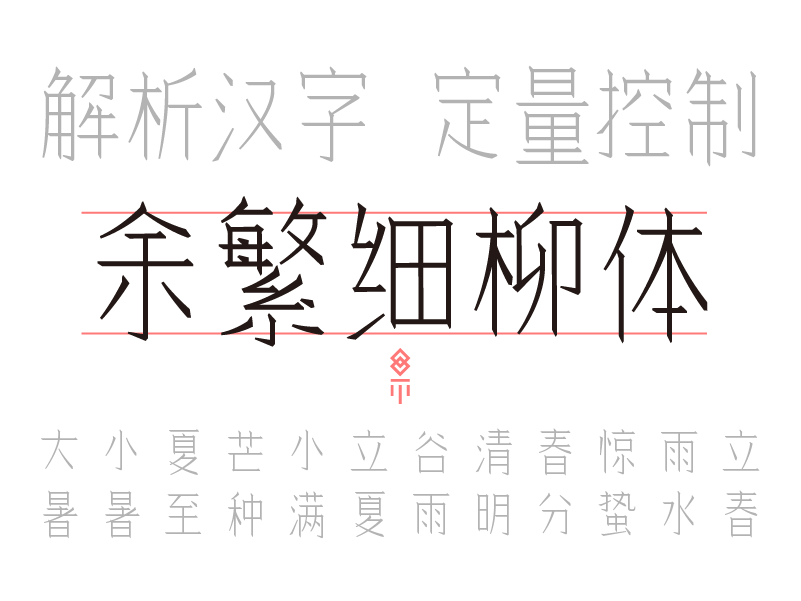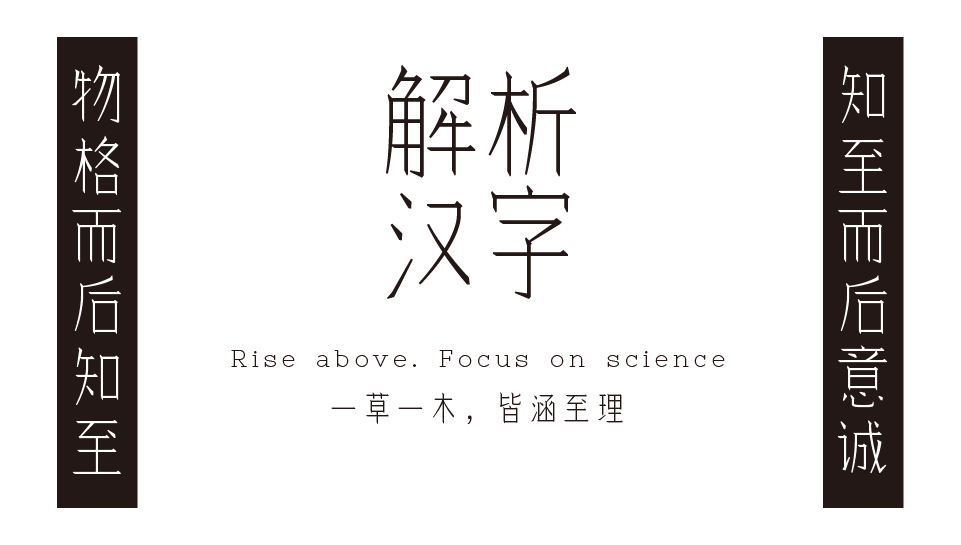
余繁细柳体
一款笔画模仿仿宋的大字面细字体。
在字高32px时,笔画宽度约为1px。所以这款字体绝不合适32px以下的字号。
设计工作十分有趣,但是校对工作太过于繁琐无聊。而且由于不是手工一个个字形制作的,一些错误字形可能存在但没有被发现。
汉字部分由动态组字系统繁星生成,元素数据 yufanxiliu.fas.json。